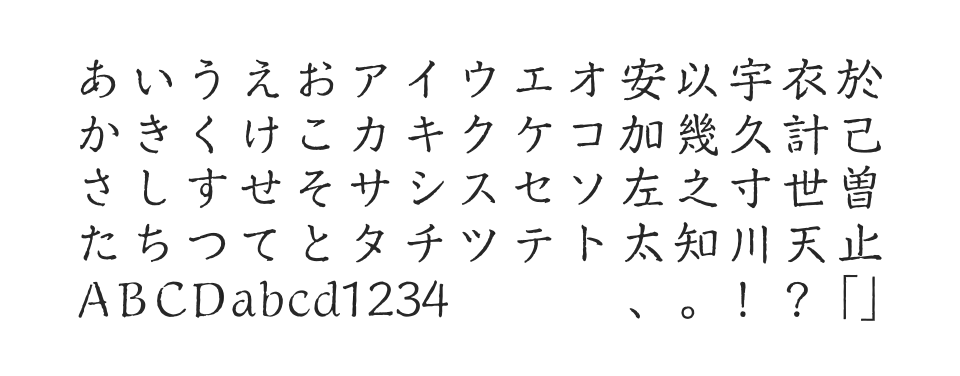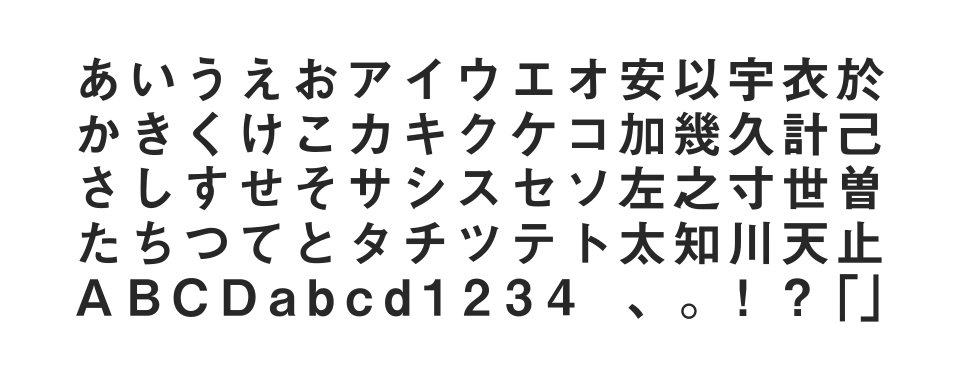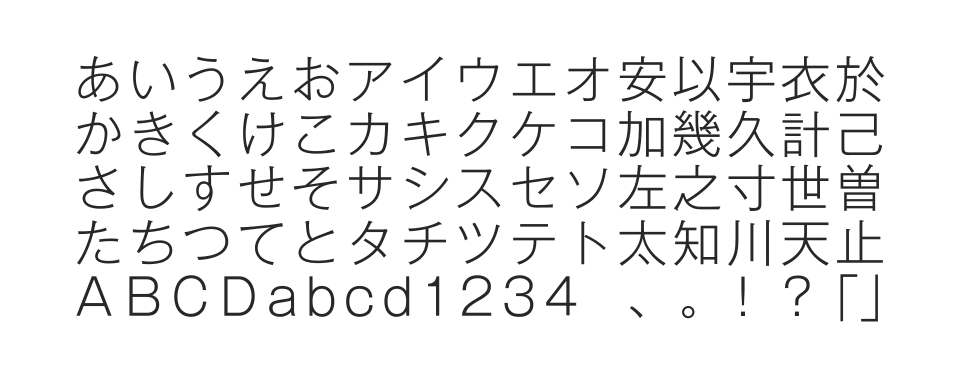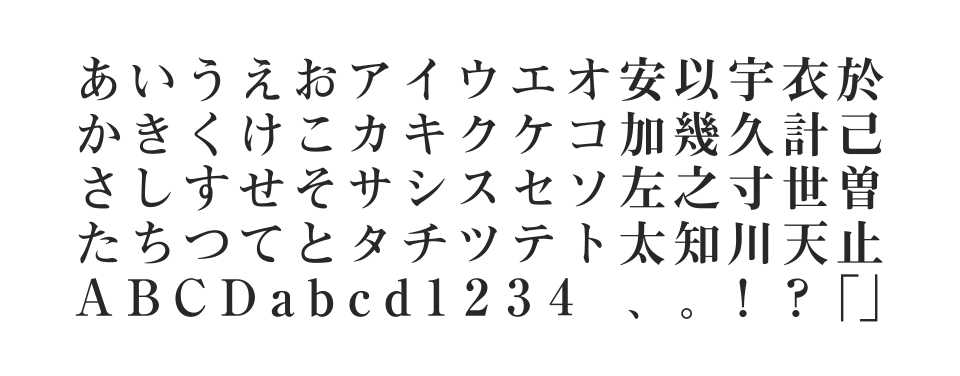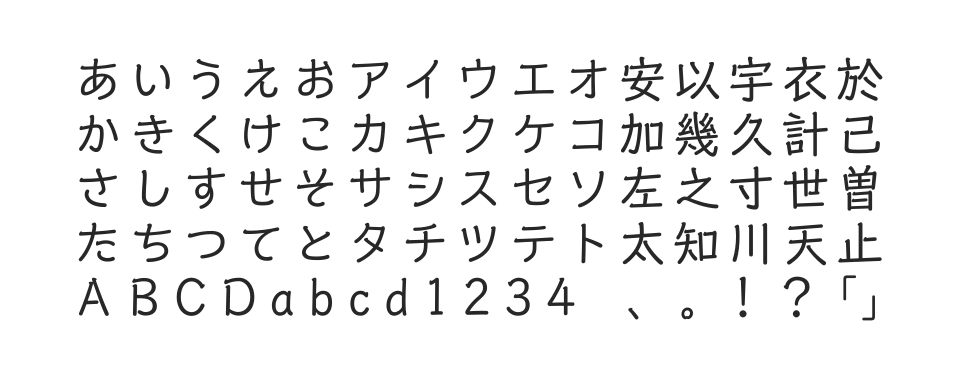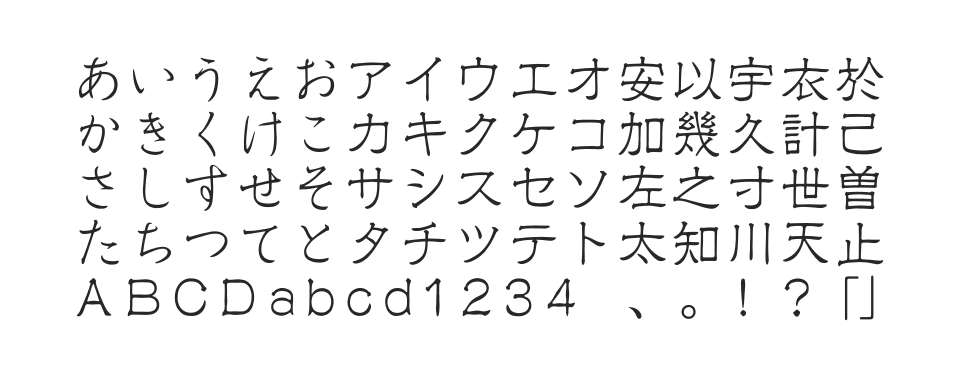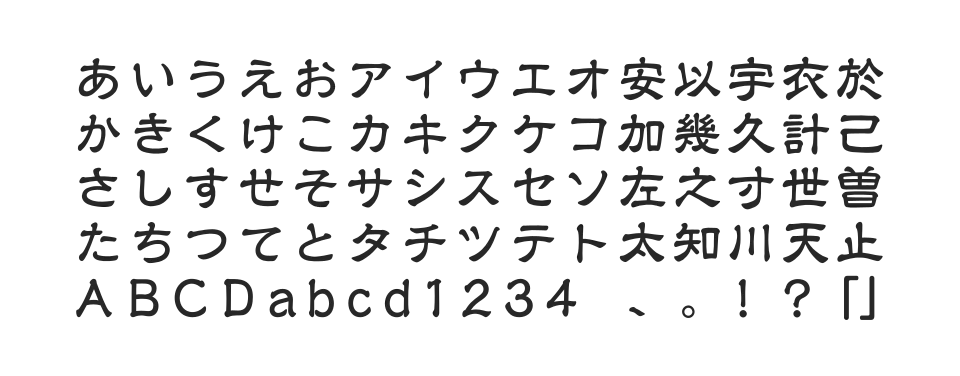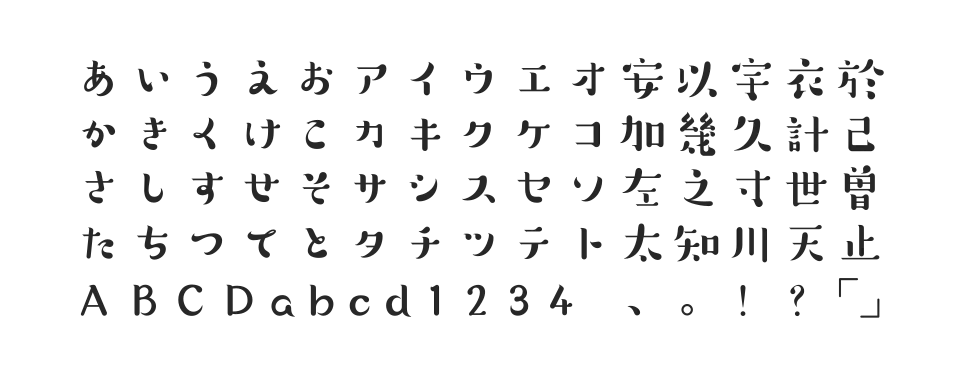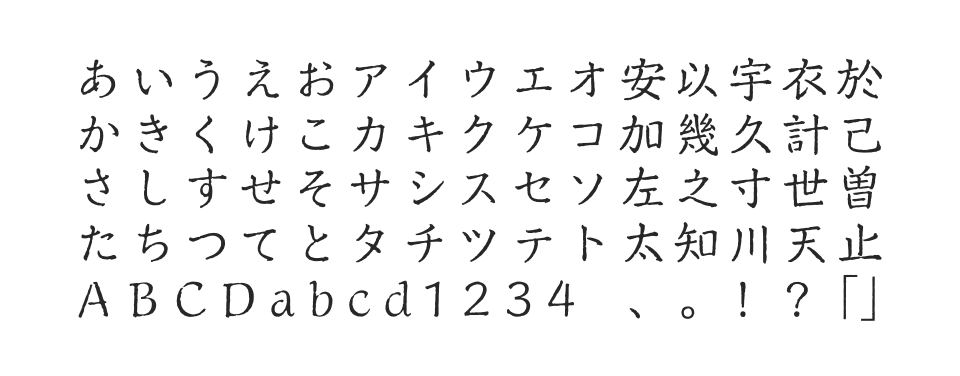
特徴的なデザイン書体。独特の字形と表現力でインパクトのある文字表現を実現。ディスプレイやキャッチコピーに適している。
タイプデザインコンペ受賞のデザイン書体。ふくよかで瑞々しい点画が親しみを感じさせ、軽妙なリズムを生む。かわいらしい印象。
正方形骨格の隷書体。縦組・横組両方で使いやすく、力強い印象の独特な字形。タイトルや見出し、ディスプレイで効果的。
伝統的な隷書体フォント。古典的な書風を現代的にアレンジした書体で、格調高い印象を与える。和風デザインに適している。
インパクトのあるデザイン書体。特徴的な字形でキャッチコピーやタイトルに適している。視覚的な印象を重視したディスプレイフォント。
見出しに最適化された明朝体フォント。力強く読みやすいデザインで、タイトルやヘッドラインに適している。AP版でペアカーニングに対応。
親しみやすいデザインのゴシック体。見出ゴMB31よりも親しみやすい印象を与える書体として、近年、出版分野でも活躍の場を広げています。
モリサワ基本7書体の一つである見出し用ゴシック体。中ゴシックBBBの筆画を太くしたようなデザインで、シャープな印象を与えることから、広告のコピー用などに数多く採用されています。
モリサワ基本7書体の一つである明朝体。伝統的な明朝体の流れを汲む書体として、長年にわたりスタンダードな明朝体として使用されています。
手になじんだ万年筆でなにげなく書き綴ったような、趣きと知性を感じさせる書体。味わいのあるにじみの表現が、手書きのタッチや紙の質感を感じさせ、文字本来の豊かな生命力が息づいています。